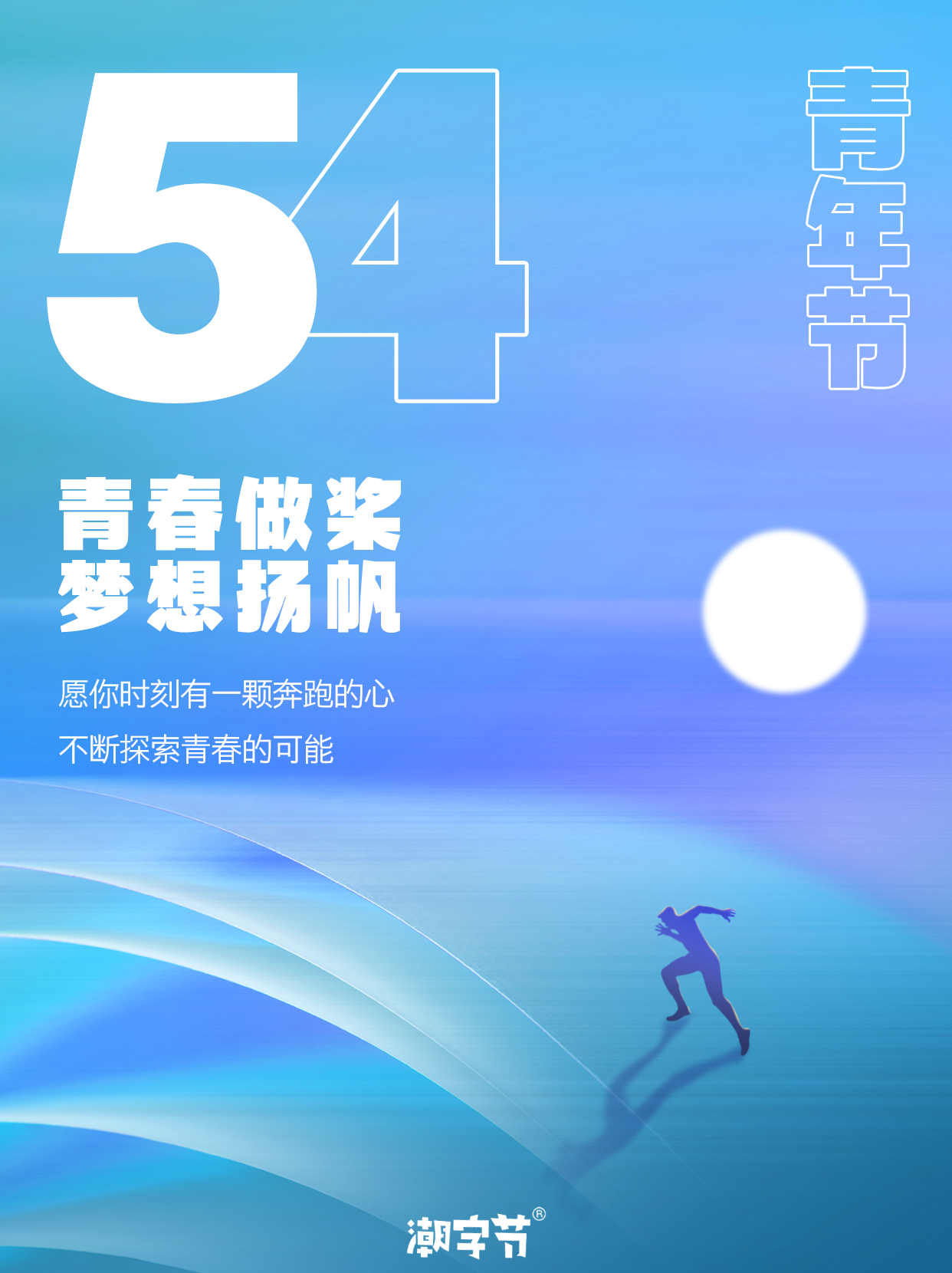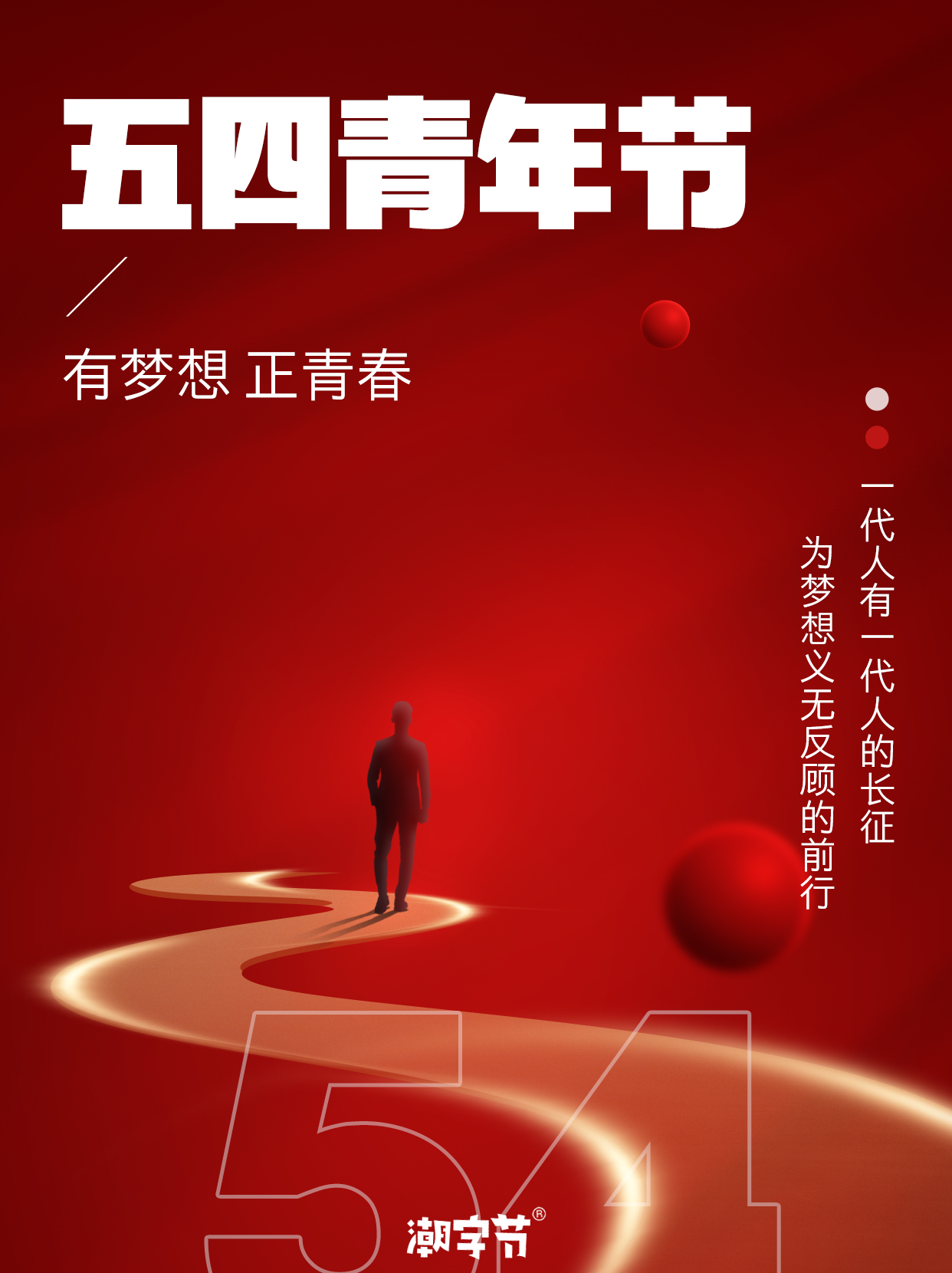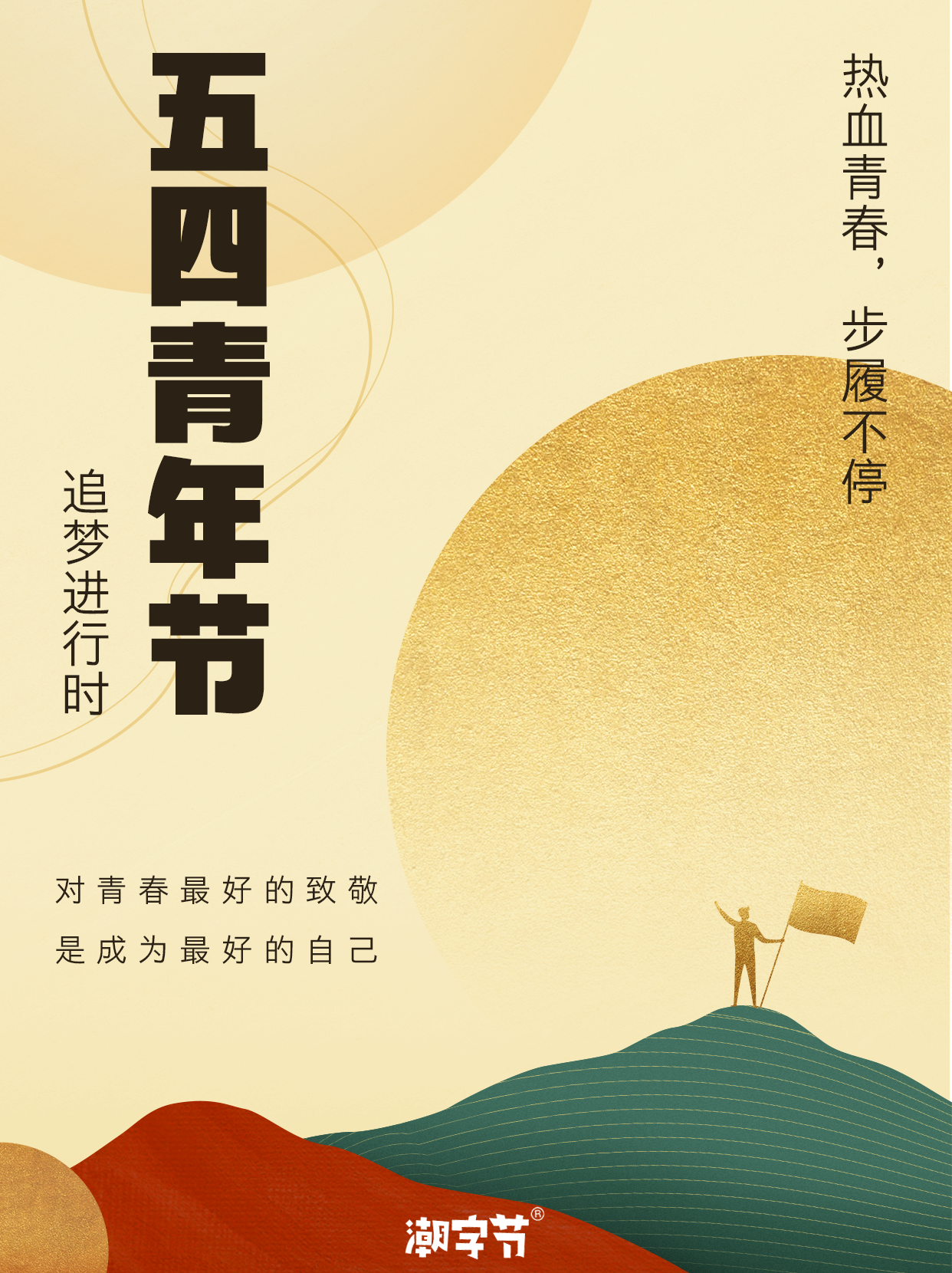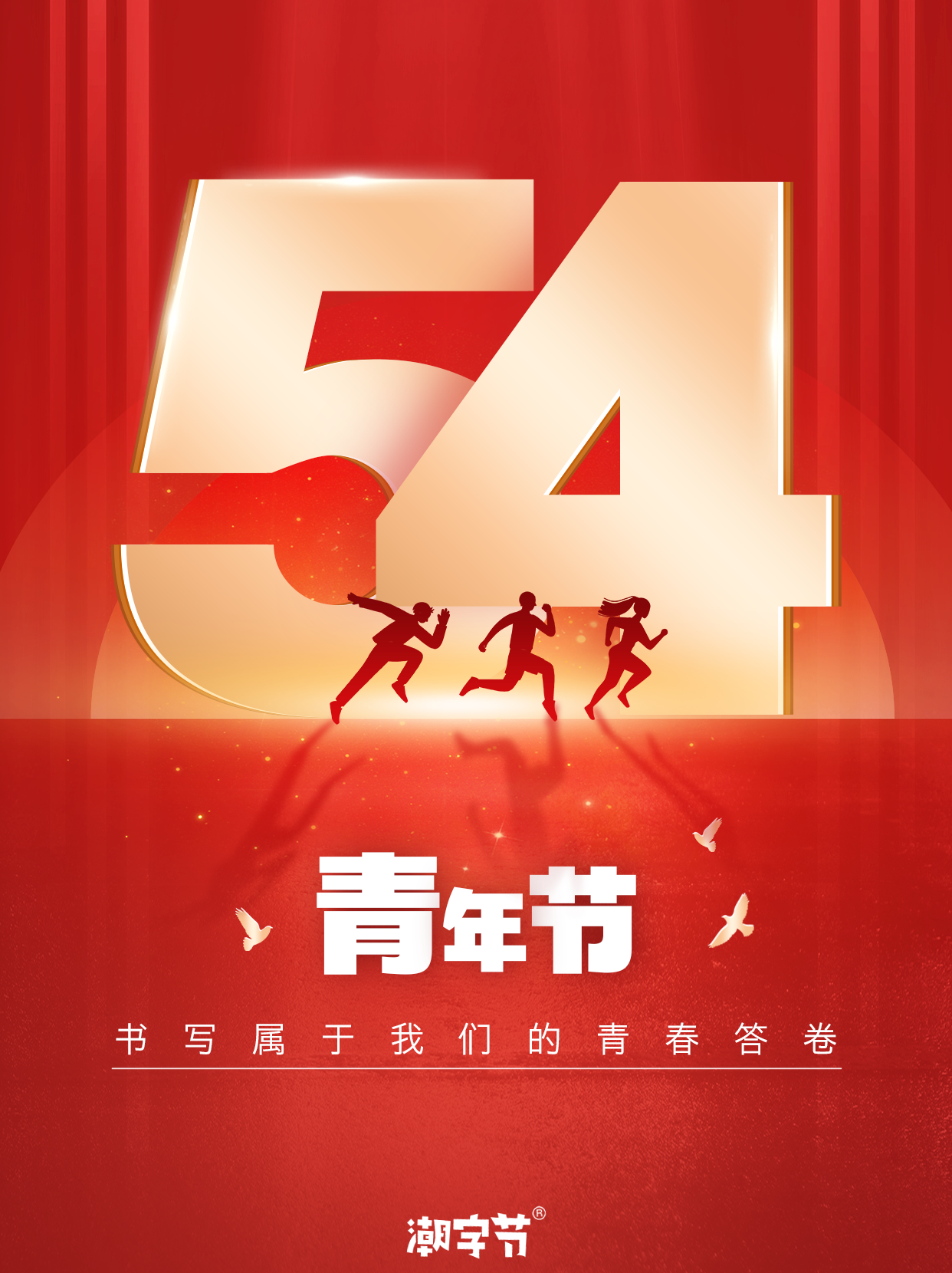
潮字节五四青年节 万人
Jump-YouthDayGB Abound
潮字节五四青年节是一款重心平稳、中宫饱满且笔画富有活力的一款黑体创意字体,它像是无论何时何地都充满了精气神,总能展现出无限的活力。这款字适合用于标题、海报等短文本,在节日场景、年轻活力的应用情况中烘托出乐观向上、生机勃勃的氛围。